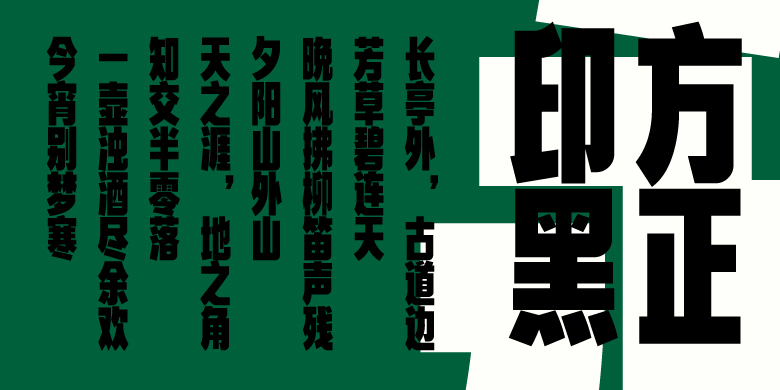
方正印黑
黑体、创意字体
方正印黑的创意来源于墙壁手写艺术字,使用厚重的笔刷,绘画出美丽且有力量的字形,字形比例为10:7,笔画处理勾的位置做了切割处理,让字形更加的棱角分明,撇捺方面保留传统黑体的柔美笔画,两者结合为一款高挑的黑体力量字。 字形适用海报主题、游戏名称、电影场景主题、电商主题标语口号、公司标准字、包装主题等等...